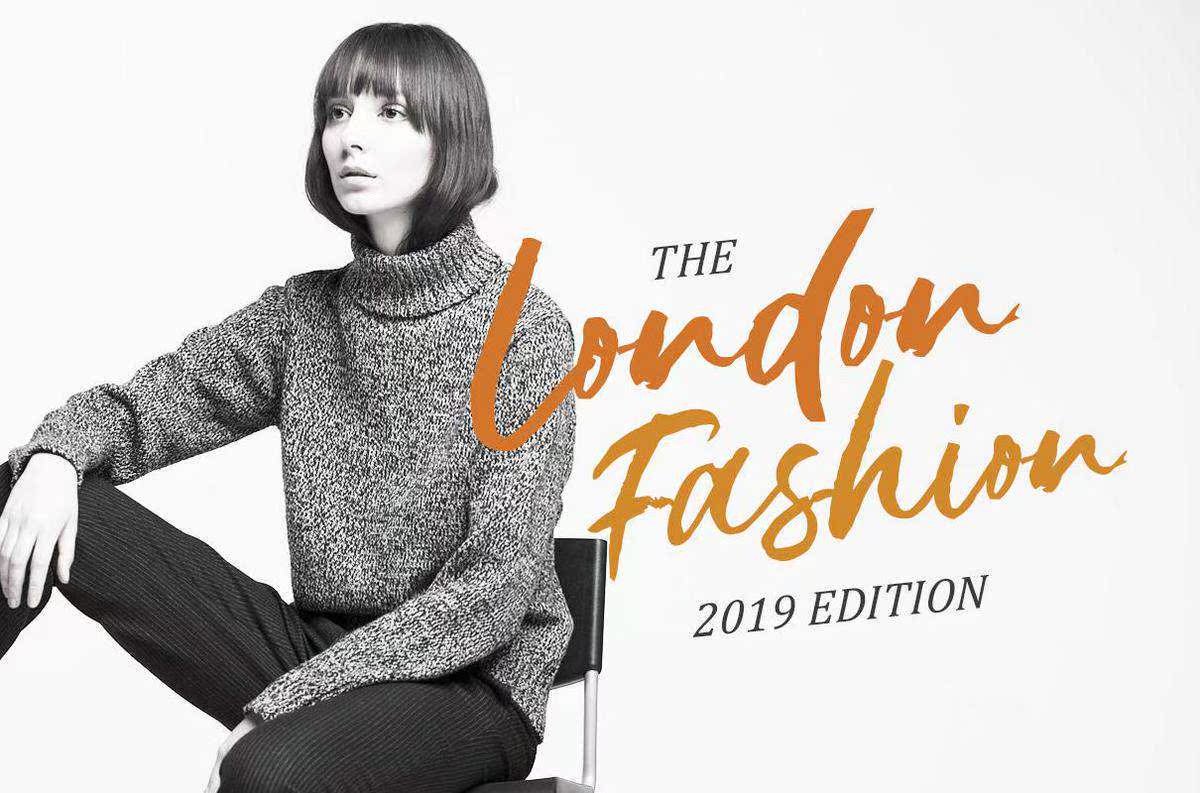
Gustolle,aSVGFont,采用混合字体书写。自然文字使字体更适合女性和男性。适合于需要标题、标识、服装、邀请、品牌、包装、广告字体的用户。该字体包括大写、小写、标点符号、符号和数字、文体设置、连字、,EtcalSo支持多语言。它也可以用UAN编码。Gustolle、aSVGFont、Madebybrush手写。自然文本使字体更适合女性和男性。适合需要字体的人,如标题、标识、服装、邀请、品牌、包装、广告等。字体包括大写、小写、标点符号、符号和数字,style setAlternate、连字等CalSoSupportMultilanguage.ItalsoalreadyPUAEncoded。